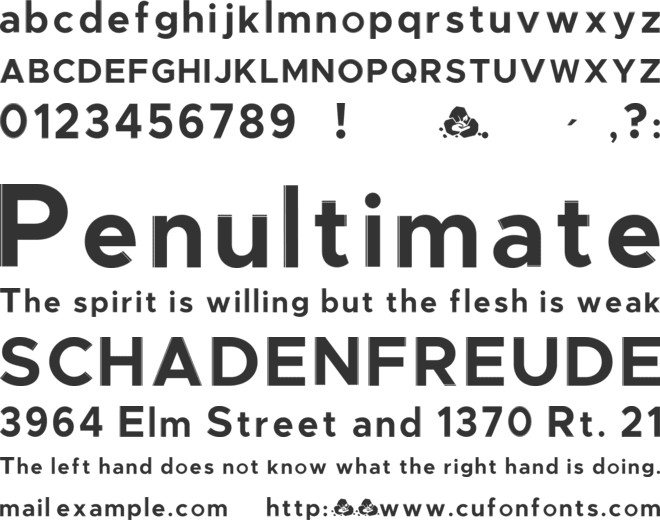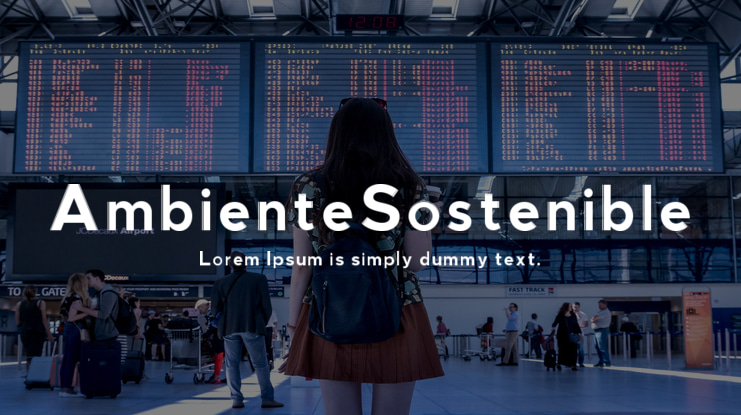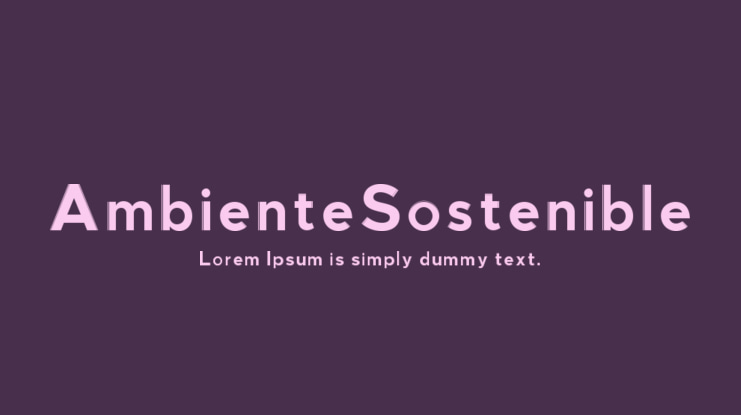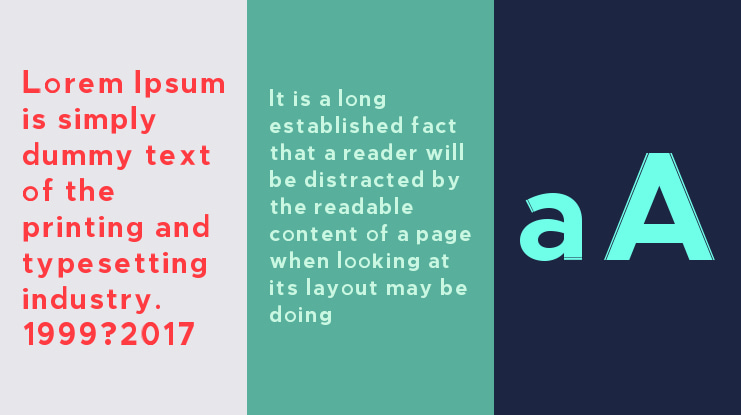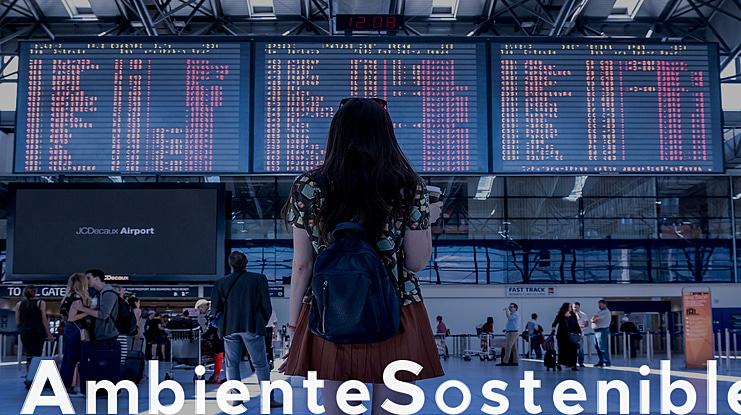
AmbienteSostenible Font
Environment J es una tipografía sans serif diseñada por los Juan David Vahos Rodríguez, diseñador gráfico.
El objetivo de esta tipografía radica en el concepto Ambiente Sostenible generando unos trazos legibles, limpios y así convertirla en una fuente atractiva.
Otro cualidad agregada es que reduce un 10% el uso de tinta y tóner a comparación de algunas familias tipográficas convencionales.
Environment J está basada en los principios de la tipografía Ryman Eco y Gotham, de uso libre.